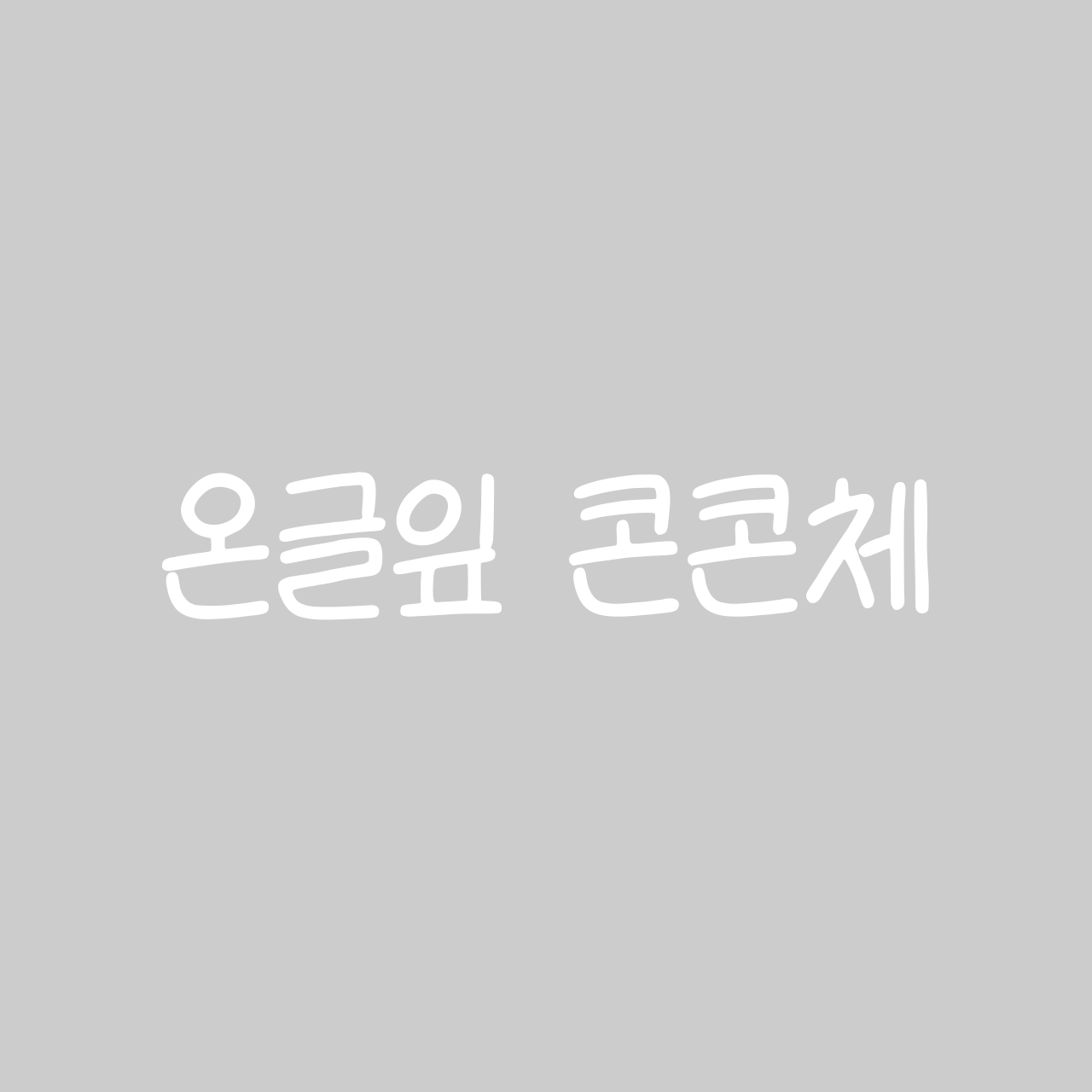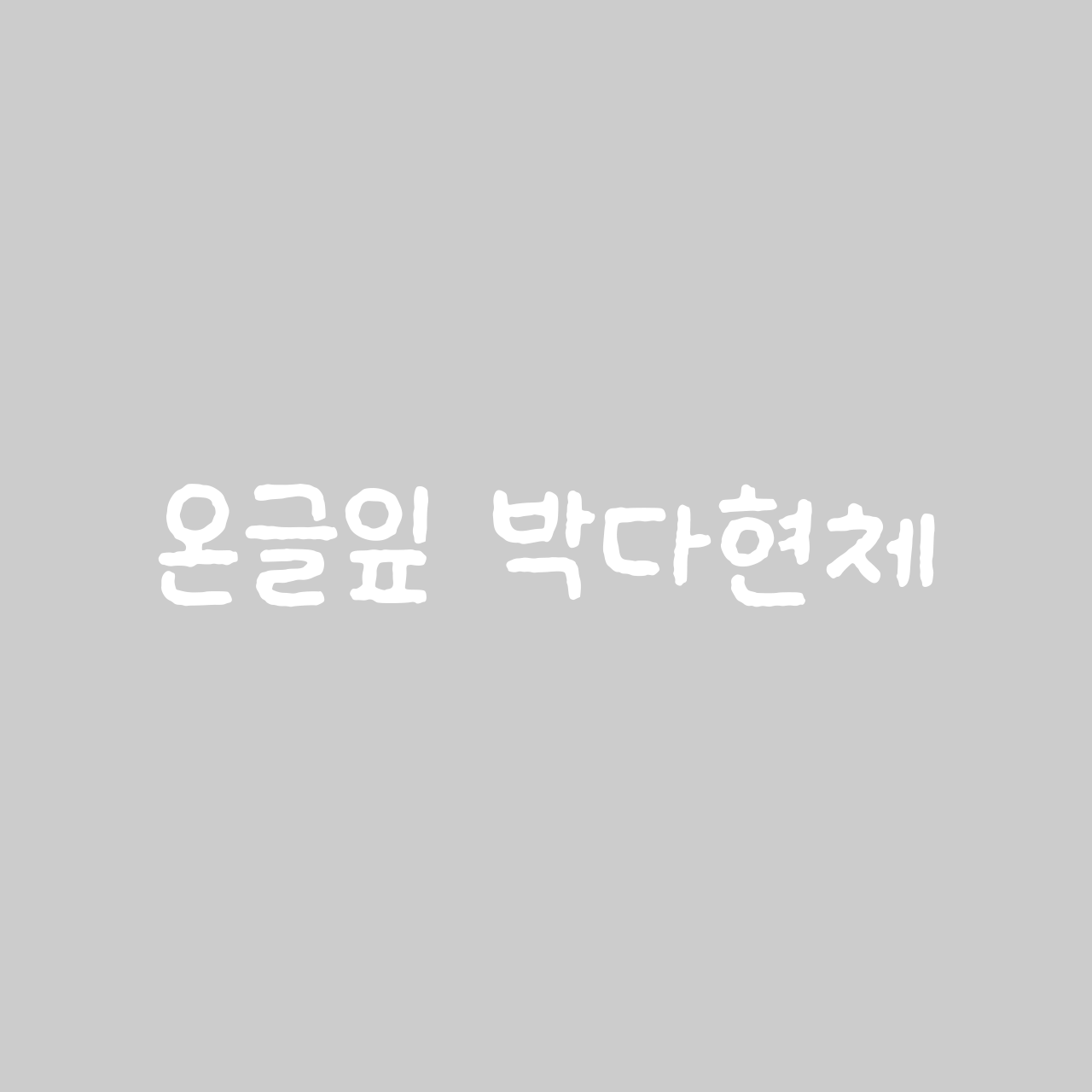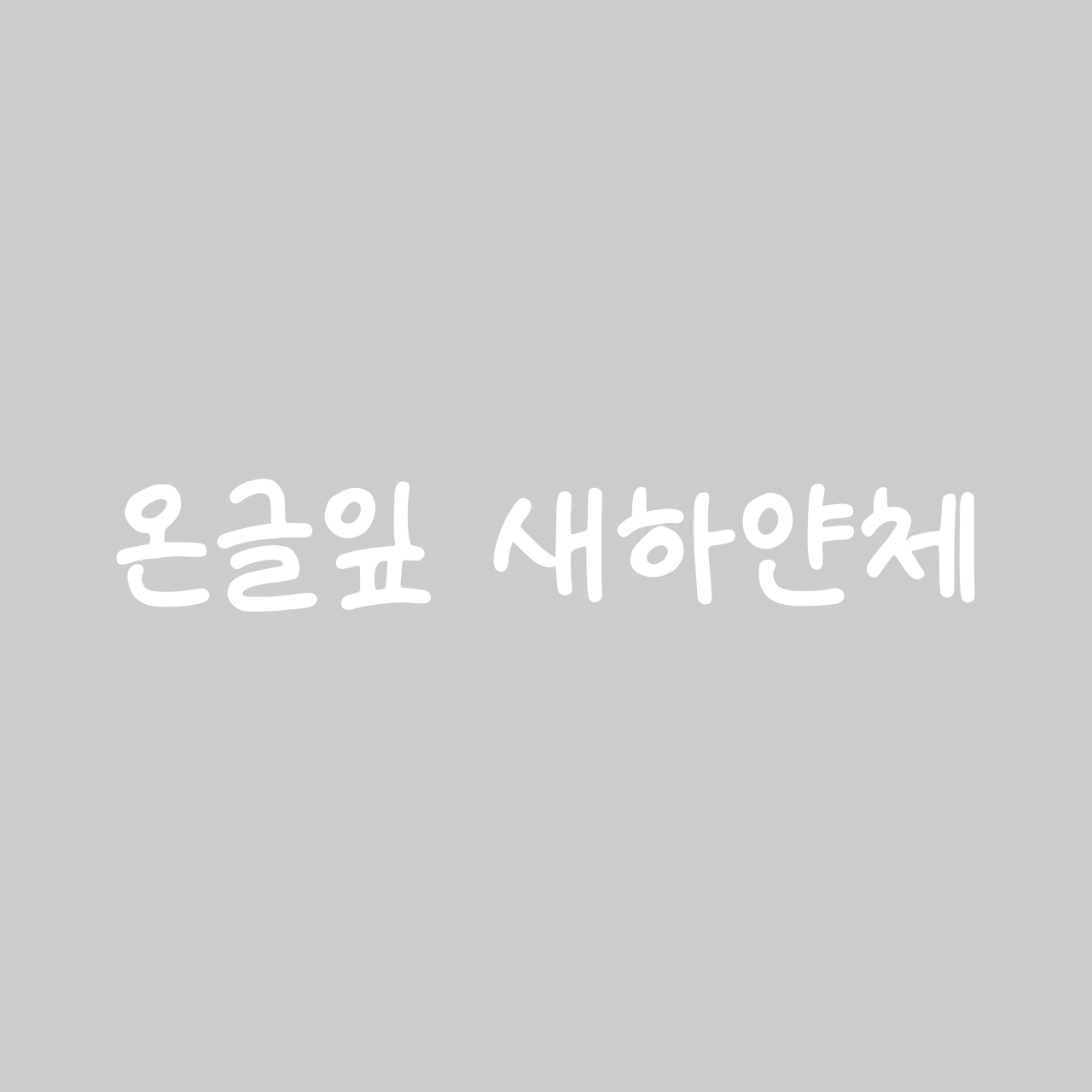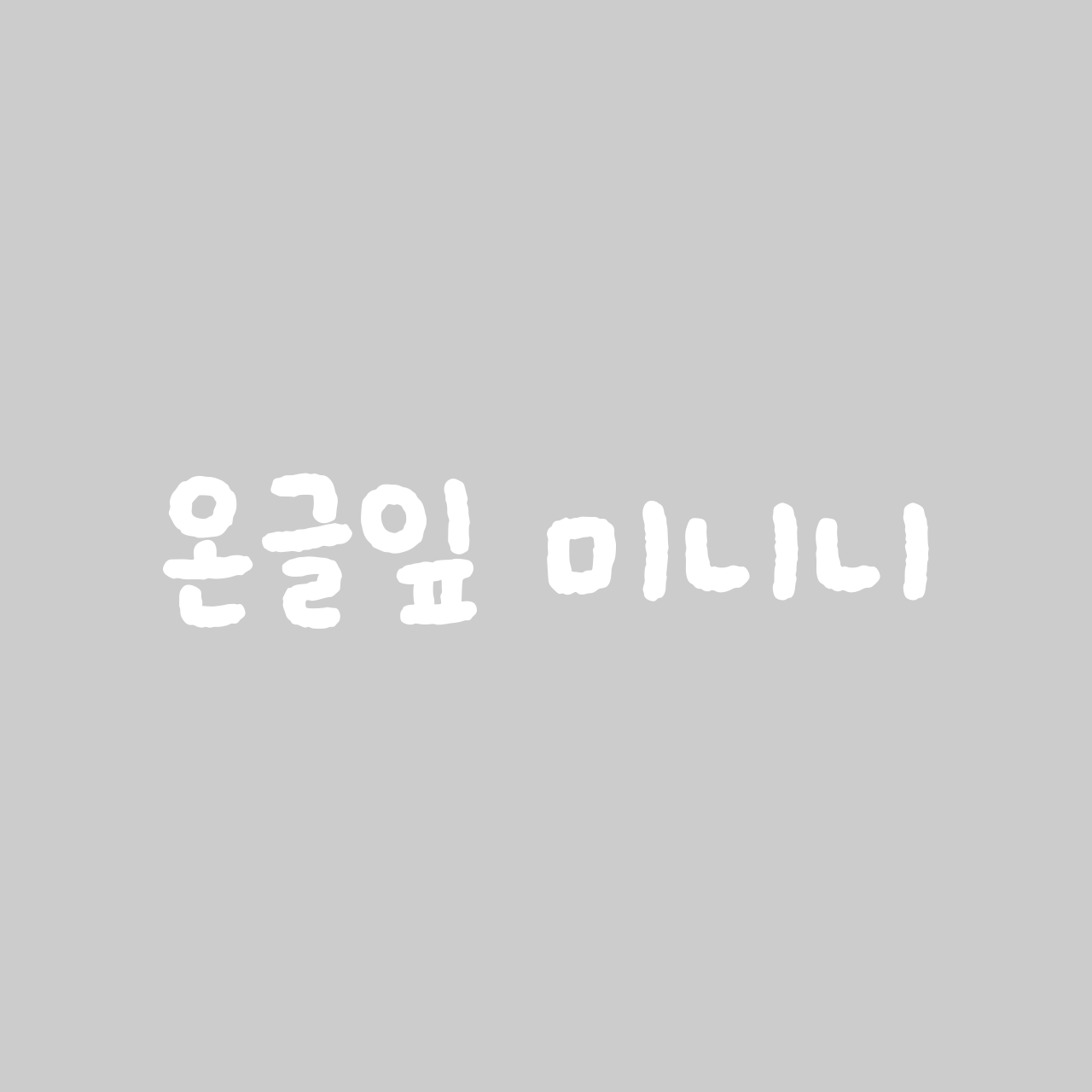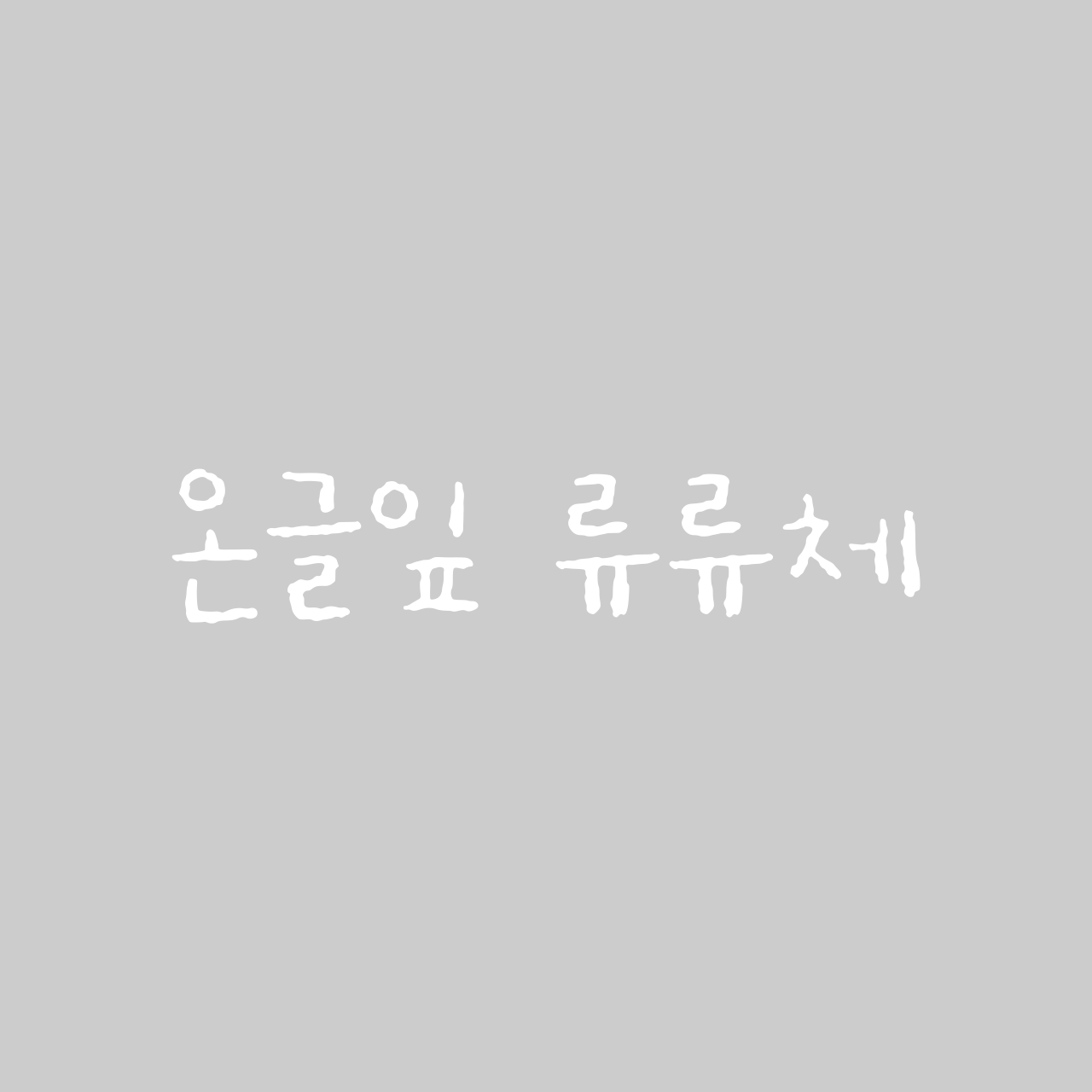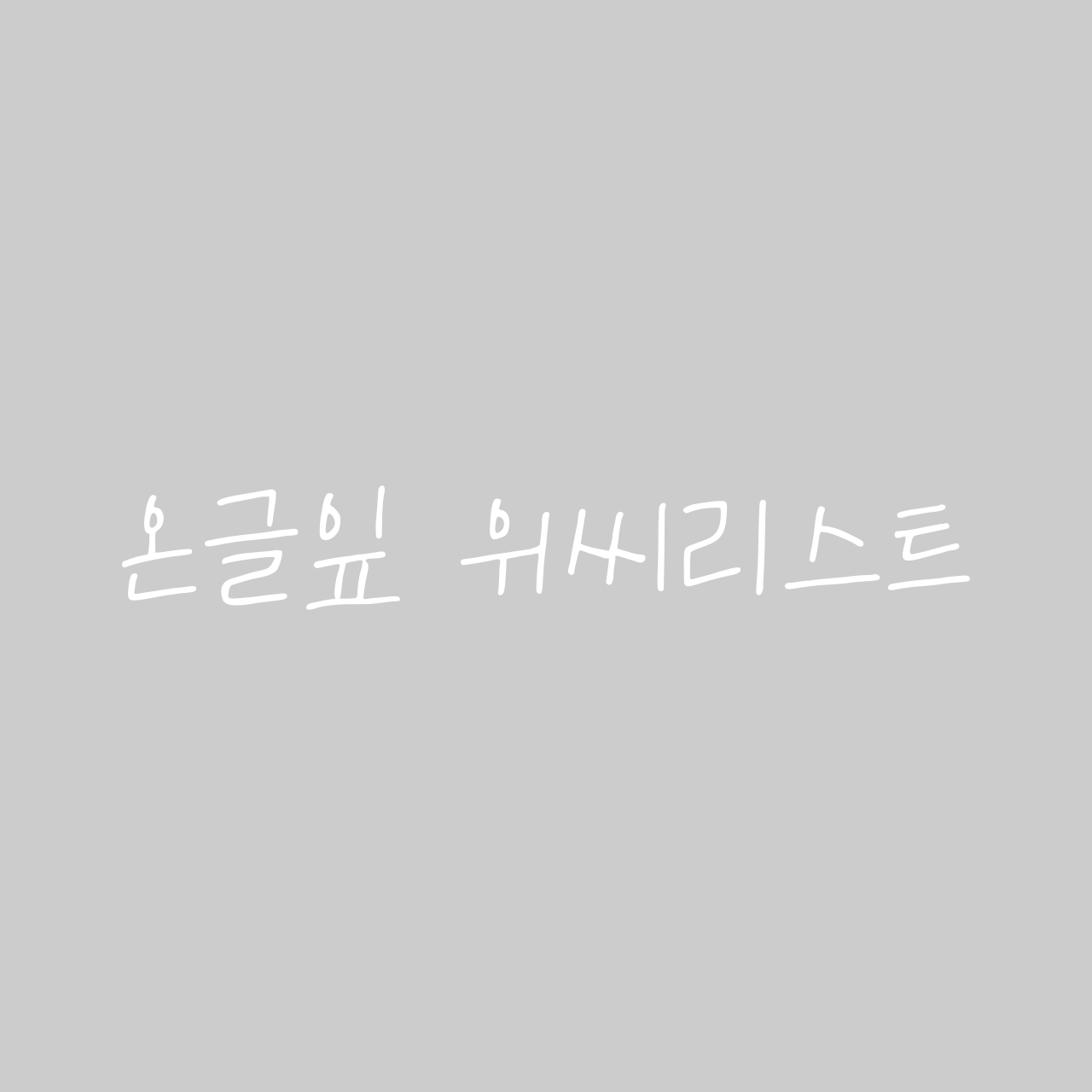
브이로그에 감성 한 스푼을 더하거나, 친근한 무드의 카드뉴스를 만들 때 우리는 손글씨 폰트를 찾게 됩니다.
특히 최근에는 AI 기술(온글잎 등)을 통해 정말 방대한 양의 손글씨가 쏟아져 나오고 있는데요. 선택지가 너무 많아 고민인 분들을 위해, 산돌구름 사용자 데이터와 트렌드를 기반으로 '실패 없는' 손글씨 폰트들을 골라봤습니다.
산돌구름 폰트찾기 게시판에서 가장 높은 문의량을 기록한 주인공은 바로 「온글잎 새하얀체」입니다.
손글씨 특유의 자소 표현이 살아있으면서도, 가독성이 전혀 떨어지지 않는다는 게 가장 큰 장점입니다. 사인펜으로 꾹꾹 눌러쓴 듯한 적당한 굵기 덕분에 정보 전달이 중요한 콘텐츠에서도 존재감을 발휘합니다.
비슷한 무드로는 어디에나 잘 어우러지는 「온글잎 해원」, 조금 더 시원시원한 공간감을 원하신다면 「온글잎 콘콘체」를 추천합니다.
온글잎 해원
다음으로 많은 분이 찾는 스타일은 펜이나 연필의 질감이 그대로 살아있는 폰트들입니다. 그중에서도 「온글잎 류류체」는 종이 위에 연필로 사각사각 쓴 듯한 느낌을 정말 잘 구현했어요.
연필 특유의 질감과 몽글몽글한 곡선이 만나 따뜻하면서도 귀여운 무드를 자아냅니다. 일기장이나 감성적인 브이로그 자막에 얹었을 때 그 진가가 드러나죠.
작고 소중한 느낌의 「온글잎 미니니」, 오밀조밀 귀여운 「온글잎 박다현체」도 추천드립니다. 필기도구의 종류에 따라 달라지는 미묘한 온도 차를 경험해 보세요.
온글잎 미니니
손글씨가 꼭 자막이나 정보 전달용으로만 쓰이는 건 아니죠. 획의 속도감이 '휙휙' 느껴지는 서체들은 타이틀이나 효과음, 강조하고 싶은 문구에 썼을 때 그 진가를 발휘합니다. 보기만 해도 청량함이 느껴지는 시원시원한 스타일들을 모아봤습니다.
「온글잎 위씨리스트」는 마치 마커나 플러스펜로 거침없이 써 내려간 듯한 에너지가 특징입니다.
여백을 시원하게 사용하면서도 글자 하나하나의 존재감이 확실해서, 화면에 생동감을 불어넣고 싶을 때 아주 유용합니다. 효과음 같은 짧은 글줄에는 투박하지만 힘 있는 「온글잎 구마 손글씨3」를 활용해 보세요.
온글잎 구마 손글씨3
지금까지 브이로그부터 카드뉴스까지, 상황에 따라 활용하기 좋은 손글씨 폰트들을 살펴보았습니다.
같은 ‘손글씨’라도 굵기, 속도감, 질감에 따라 전달되는 분위기가 크게 달라지는 만큼, 콘텐츠의 결에 맞는 선택이 중요합니다.
어떤 폰트를 써야 할지 고민될 때, 오늘 소개해 드린 기준을 참고해 하나씩 시도해 보시면 자연스럽게 ‘나에게 맞는’ 폰트를 찾으실 수 있을 거예요.